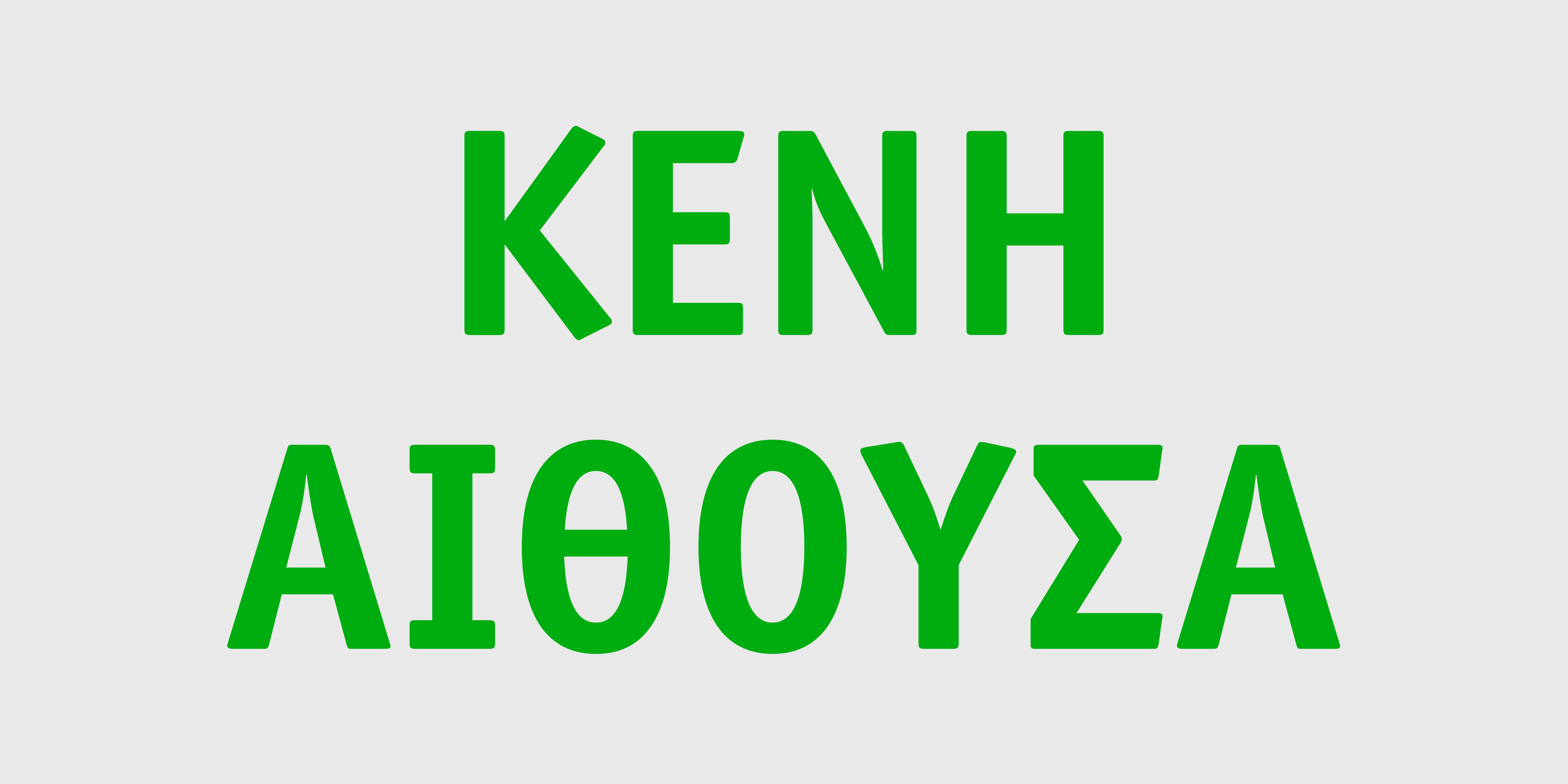
Officina Sans ITC Ελληνικά
Η ITC Officina σχεδιάστηκε ως μία οικογένεια γραμματοσειρών ιδανική για όλες τις δουλειές ενός γραφείου (εκτύπωση, αλληλογραφία, επαγγελματική τεκμηρίωση);. Αποτελείται από σχετικές μεταξύ τους εκδοχές, τη serif και sans serif. Η αναλογία του σχεδίου είναι ελαφρά στενή για να βοηθά στην εξοικονόμιση χώρου, ενώ τόσο οι απολήξεις όσο και οι πατούρες έχουν σχεδιαστεί με τέτοιο τρόπο ώστε να ανταποκρίνονται στις ενδεχόμενες απώλειες που προκύπτουν από τη χαμηλή ανάλυση εκτύπωσης ενός εκτυπωτή, φαξ, ή την υφή ενός απλού χαρτιού. H ITC Officina γεφυρώνει την απόσταση μεταξύ γραμμάτων παλιάς γραφομηχανής και πιο παραδοσιακού τυπογραφικού σχεδιασμού. Το ύφος της είναι αυτό που συναντάται σε μια παραδοσιακή γραφομηχανή, τροποποιημένο κατά τέτοιο τρόπο ώστε να ταιριάζει με τις σύγχρονες τεχνολογικές εξελίξεις. Τόσο οι ισόπαχες όσο και ανισόπαχες γραμματοσειρές είναι σχεδιασμένες και στοιχισμένες με τέτοιο τρόπο που να προσφέρεται η μεγαλύτερη δυνατή αναγνωσιμότητα.